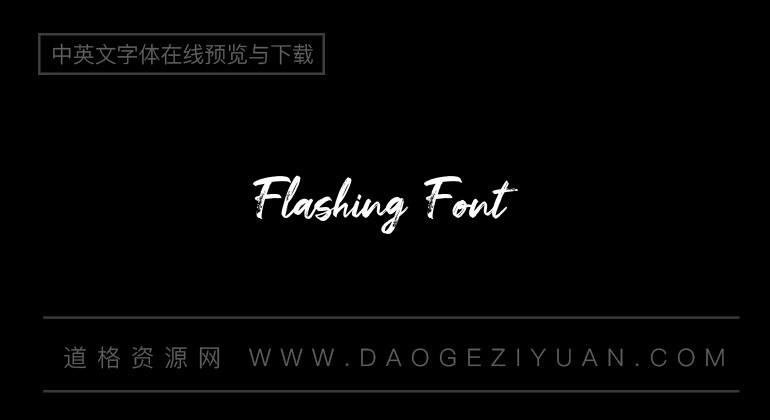
Flashing Font
Flashing Font 字体是一种特殊的字体,具有闪烁的动态效果,常用于网页设计、数字游戏、广告宣传等场合。它通常由一系列字形构成,每个字形都包含了多个帧(frame)的动画效果,通过不断切换不同帧,就能够呈现出字体的闪烁效果。 Flashing Font 字体通常使用在需要吸引用户注意力的场合,如网页标题、广告标语等,能够增加页面或广告的视觉冲击力,提高用户点击率。但由于其特殊的设计风格,一般不适合用于正式文档或商务信函等正式场合。
Flashing Font是一款非常不错的手写艺术字体,具有很好的视觉感,适合于文化类的宣传设计、商业类品牌的广告和产品包装设计以及个性化文字排版等较多场景。